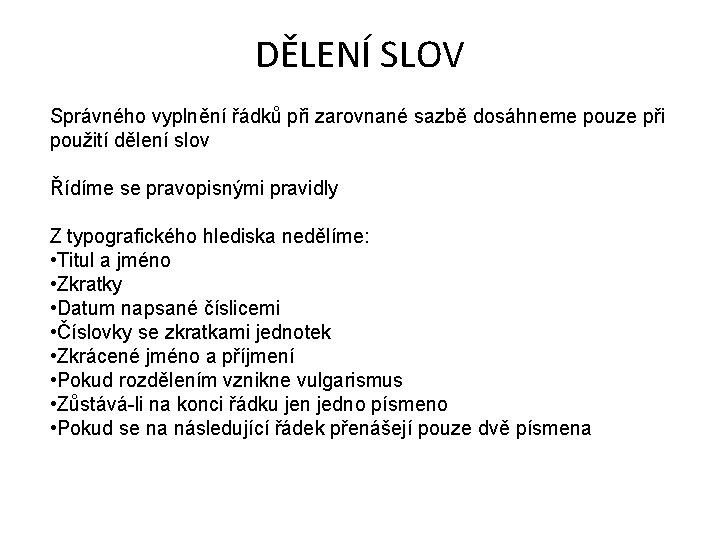
TYPOGRAFIE • práce s písmem a jeho uspořádání v grafických projevech • zajišťuje čtenáři snazší čtení • hledá způsoby jak docílit, aby tok informací unavil oči co nejméně • nejdůležitější vlastností textu je bezvadná čitelnost, ostatní, jako originalita nebo tvarová výjimečnost, nabývají významu jen ve specifických případech (logotyp, titul knihy apod. ).
TYPOGRAFICKÁ PRAVIDLA • Jednoznakové předložky je nutné odstranit z konců řádků • Nevytvářet kurzívu umělým skloněním v určitém úhlu • Čárka a pomlčka se neklade za číselnou hodnotu měny (25 Kč). Výjimkou je případ, kdy je značka měny před číslem (Kč 35, -) • Pomlčka ve významu „a“, „až“, „od“, „do“ se neodděluje mezerou (8 -12 hodin). • Značka (%) se odděluje mezerou (padesát procent = 50 %). Pokud jde ale o přídavné jméno, značka se mezerou neodděluje (padesátiprocentní = 50%).
DĚLENÍ SLOV Správného vyplnění řádků při zarovnané sazbě dosáhneme pouze při použití dělení slov Řídíme se pravopisnými pravidly Z typografického hlediska nedělíme: • Titul a jméno • Zkratky • Datum napsané číslicemi • Číslovky se zkratkami jednotek • Zkrácené jméno a příjmení • Pokud rozdělením vznikne vulgarismus • Zůstává-li na konci řádku jen jedno písmeno • Pokud se na následující řádek přenášejí pouze dvě písmena
ČÍSLA A ZKRATKY • Číselné hodnoty v textu sázíme slovně • Tisíce a milióny oddělujeme mezerou • Desetinná místa se oddělují čárkou bez mezery • Čísla ve sloupcích musí mít nad sebou jednotky desítky i stovky Telefonní čísla tvoří skupiny po dvou až třech a nesmí se dělit do dvou řádků • Zkratky akademických titulů končí tečkou a jsou psány podle pravopisných pravidel • Stupeň nemá svoji klávesu, ale nemůžeme ho nahradit deformací jiného znaku
ZVLÁŠTNÍ KAPITOLU TVOŘÍ TYPOGRAFIE PRO WEB • Obtížně se zde dodržují pravidla české typografie • Výběr fontů je omezen na písma dostupná na počítači přihlášeného • Pokud se jedná o dokument dlouhodobého významu je dobré jeho úpravě věnovat dostatek času